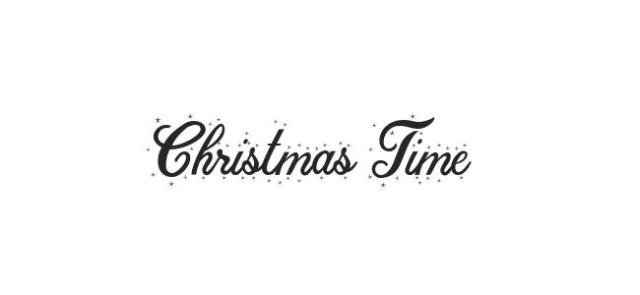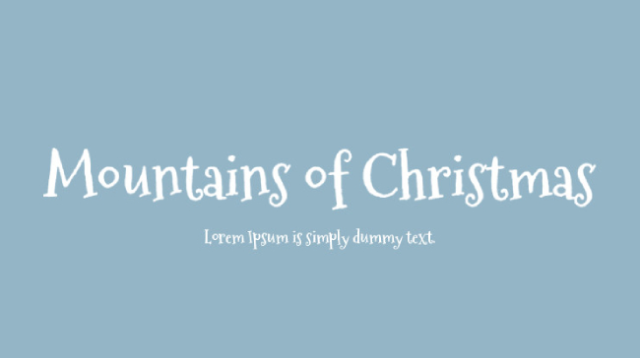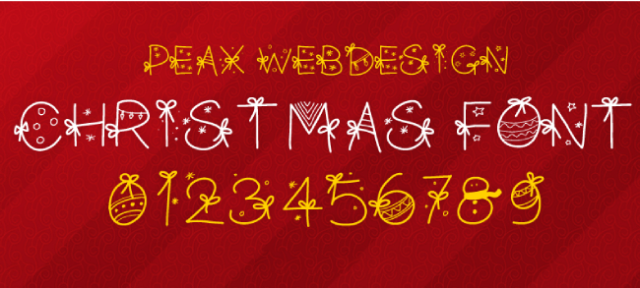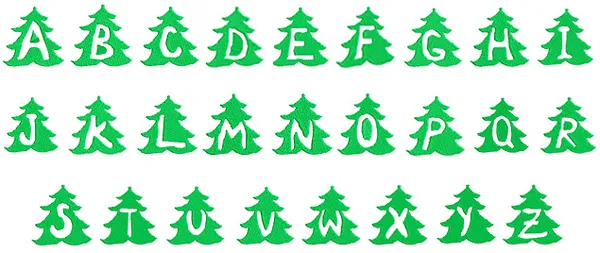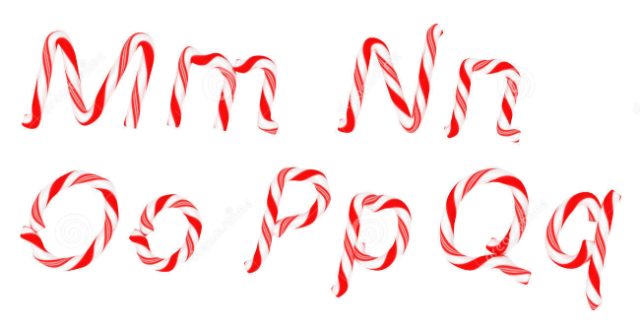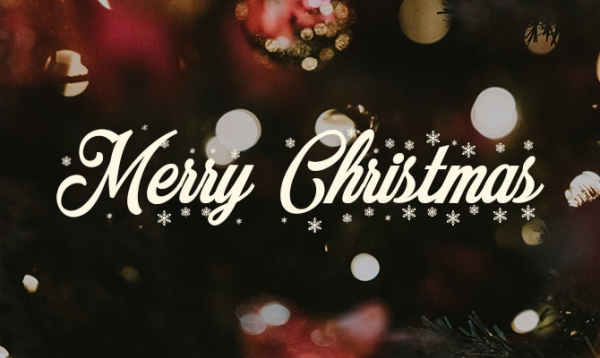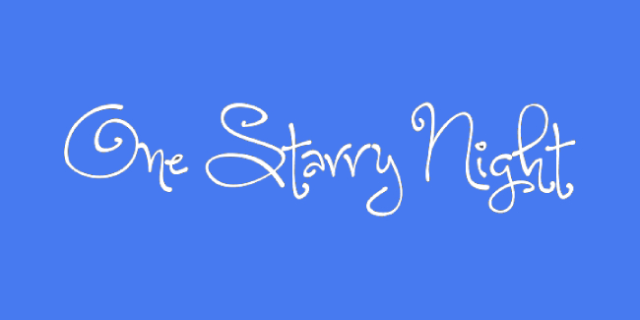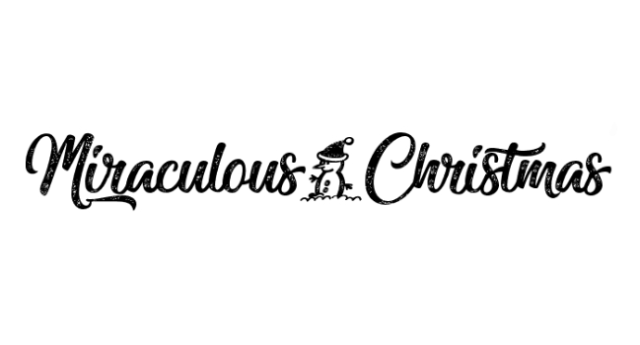
15 Font Natal Gratis Terbaik untuk Semua Desain Liburan Anda
Diterbitkan: 2021-12-20Natal adalah tentang penerangan, harapan, kue, hadiah, dan banyak lagi. Saat kita mendekorasi sekeliling selama Natal, dengan cara yang sama, kita perlu mendesain situs web kita dengan Font Desain Natal gratis sehingga seperti Malam Natal, situs web kita juga, membuat mata kita berbinar.
Seperti dekorasi yang diperlukan selama Natal, dekorasi diperlukan selama pembuatan web. Font X-mas wajib untuk membuat website digital, kartu pos, pakaian adat, piring dengan pesan tercetak dan sebagainya.
Membuat semua hal terkait seperti itu seperti menyiapkan hadiah untuk pelanggan. Santa membagikan hadiah kepada semua simpatisan, serupa dengan cara, kami juga dapat memberikan hadiah dan voucher kepada pelanggan kami melalui font, desain, tata letak yang indah ini.
Di sini, di blog ini, saya akan menunjukkan kepada Anda beberapa dari 15 Font Natal gratis terbaik untuk semua desain liburan Anda. Ayo, mari kita lihat:
15 Font Natal Gratis Terbaik untuk Semua Desain Liburan Anda
1. Malam Natal :
Saya akan mulai dengan Malam Natal, semua karena Natal dimulai dengan malam Natal. Font ini adalah salah satu font gratis Natal yang paling banyak digunakan untuk semua desain liburan Anda.
Ini memberi Anda banyak detail terkait Natal, penerangan, kilau, pohon Natal kecil, dan banyak lagi. Font ini dapat digunakan untuk desain besar di website Anda seperti heading, logo, title. Coba font Malam Natal ini dan hiasi situs web Anda.
2. Satu Malam Berbintang :
Untuk pengagum lingkaran dan twirls, berikut adalah gaya font One Starry Night yang sangat mewah dan menarik perhatian. Terlepas dari kenyataan bahwa font tersebut sangat dijelaskan dalam rencananya, seseorang benar-benar dapat dipahami.
Berfungsi dengan baik untuk judul pendek dan dapat diakses dalam huruf besar, huruf kecil, angka, dan beberapa gambar. Font-nya menakjubkan, memanjakan mata, Getty dan bekerja dengan baik untuk semua desain liburan Anda.
3. Natal yang Ajaib:
Ajaib seperti namanya, keajaiban, font ini bahkan menambahkan kualitas manusia salju untuk menambahkan keceriaan liburan ekstra ke situs web Anda. Miraculous Christmas adalah font kursif, mudah dibaca dan memberikan pilihan yang bagus untuk logo.
Huruf yang dibuat dan dirancang dengan indah, dan simbol manusia salju membuat font ini sangat menggemaskan sehingga orang tidak dapat menahan diri untuk tidak menggunakannya.
4. Pohon Natal :
Pohon Natal seperti namanya, termasuk pohon-pohon kecil yang indah di dalam pohon itu, setiap huruf abjad disertakan. Font pohon Natal tidak hanya digunakan untuk liburan musim dingin tetapi juga untuk semua jenis situs web.
Ini mencakup dan memberikan dampak pohon dan alam. Pepohonan berwarna hijau dengan huruf-huruf di dalamnya.
5. Kartu Natal :
Tampilan vintage seperti cinta pada pandangan pertama dalam kasus saya. Saya seorang pecinta koleksi antik hati. Ketika berbicara tentang kartu hadiah atau kartu vintage, oh my, itu seperti ceri di kue atau kue prem dengan kopi di malam Natal.
Saya cukup terkesan dan senang dengan font yang saya temukan yang digunakan dalam kartu pos berabad-abad yang lalu. Sulit untuk membuat ulang font vintage itu secara manual, seseorang perlu mempelajari tipografi atau kaligrafi untuk itu.
Kartu Natal ini memberi Anda satu premade di mana Anda dapat membuat teks apa pun dengan gaya kuno. Font Natal gratis terbaik ini akan memberikan tampilan berkelas ke situs web Anda untuk semua desain liburan Anda.
6. PW Natal :
PW Christmas, saya sebut saja cutie pie sebagai nama lain. Setiap alfabet, huruf, angka, karakter khusus berpakaian seolah-olah mereka semua mengadakan pesta. Pencahayaan, busur, klip, bintang, dan berbagai desain yang digunakan dengan setiap huruf.
Font ini lebih cocok untuk judul header atau elemen besar lainnya, tidak baik digunakan sebagai teks isi atau item menu. Sekali lagi, font PW Christmas gratis untuk penggunaan pribadi dan dikenakan biaya untuk penggunaan komersial. Jadi untuk penggunaan komersial, seseorang harus menghubungi pembuat font.
7. MTF Santa yang Terhormat:
MTF Dear Santa adalah tentang representasi Natal. Gaya teks khusus ini menyoroti Santas yang lucu, camilan, dan rusa kutub yang menggemaskan. Surat-surat itu sendiri tampaknya seperti Comic Sans, namun, kita dapat memaafkan pelanggaran itu karena penggambarannya yang unik.
Alih-alih sebagian dari font alternatif yang telah kami soroti, font ini lebih mudah dipahami dan karenanya dapat digunakan di beberapa komponen situs juga, termasuk simbol dan menu.
8. Selamat Natal :
Font Merry Christmas terdiri dari rusa kutub, bintang, penerangan, huruf kursif, dan berbagai simbol dan karakter khusus lainnya.
Kesimpulan:
Ada lebih banyak font Natal yang tersedia di pasar, tetapi di sini, di artikel ini, saya telah menyebutkan beberapa font yang paling banyak digunakan dan berorientasi pada hasil terbaik dan kreatif.
Font Natal ini akan membantu Anda membuat desain situs web Anda lebih kreatif, inovatif, memukau, dan indah. Coba font Natal yang terdaftar ini untuk semua desain liburan Anda.